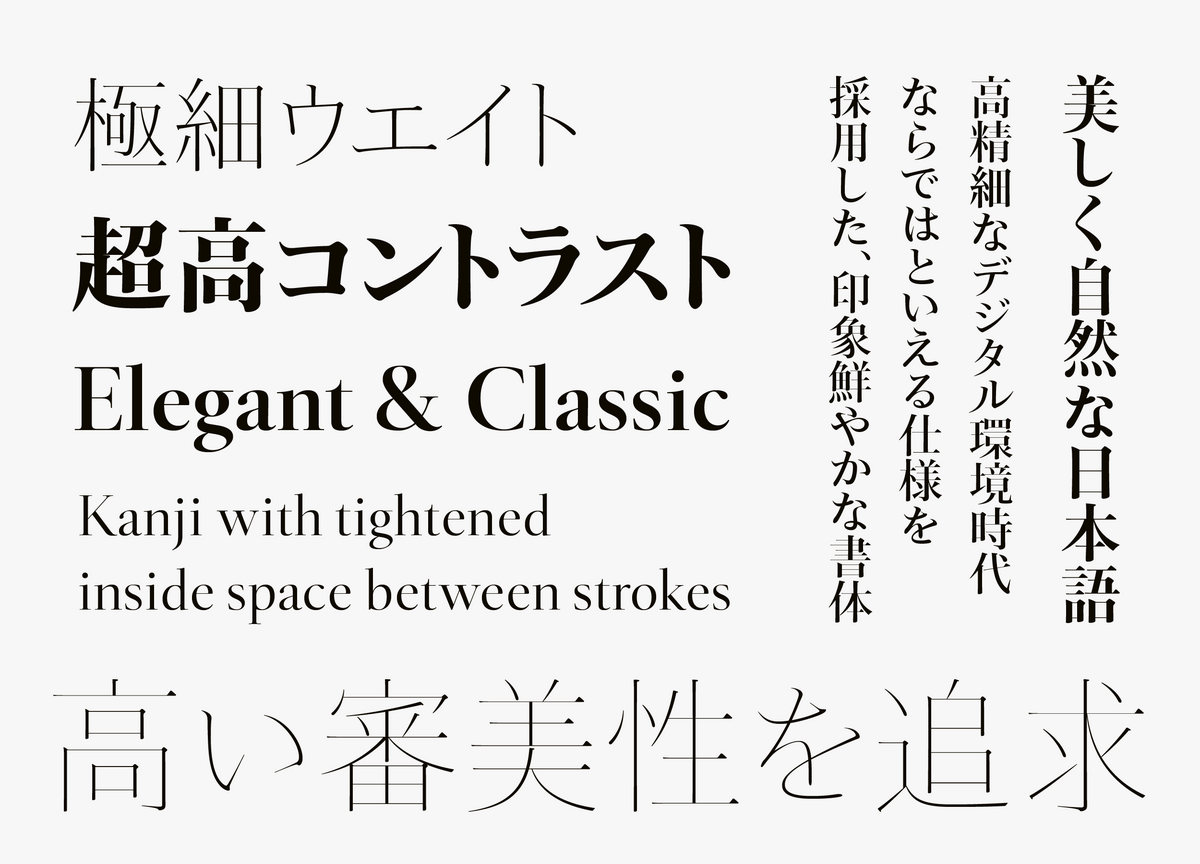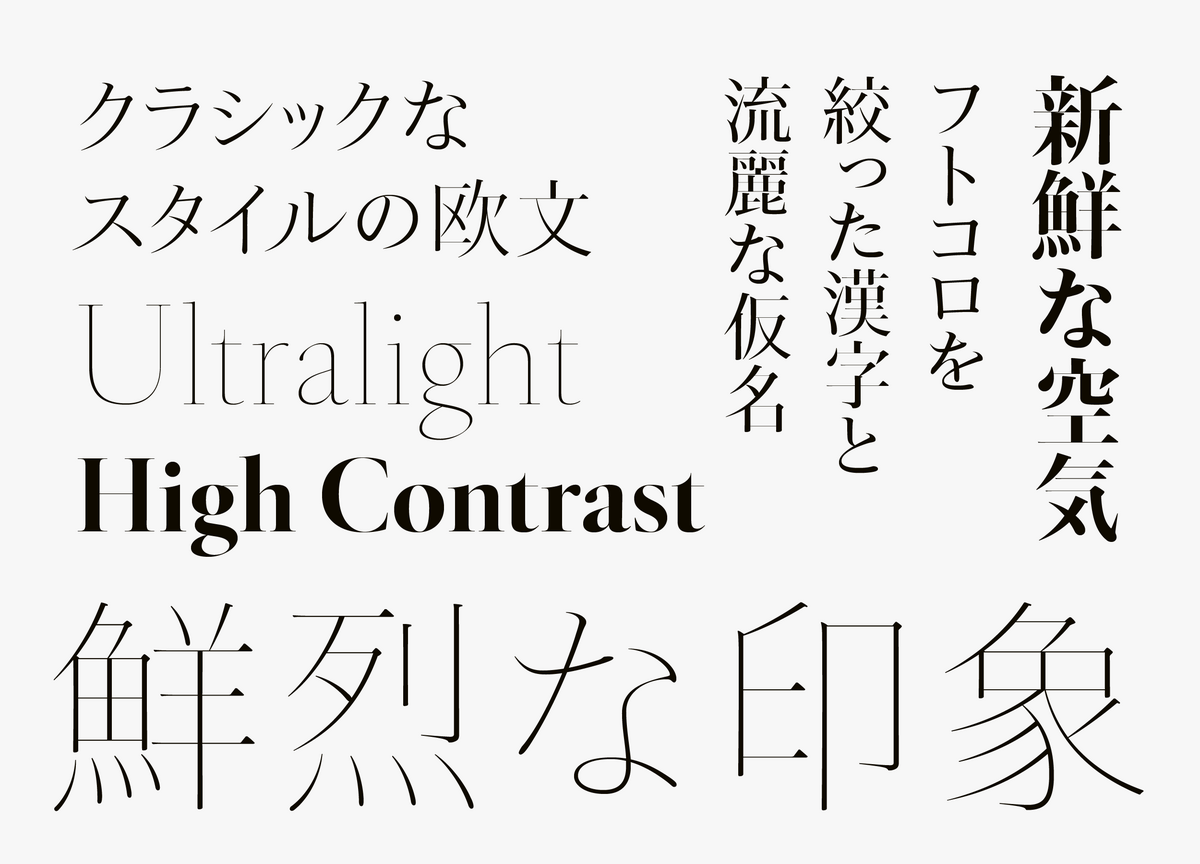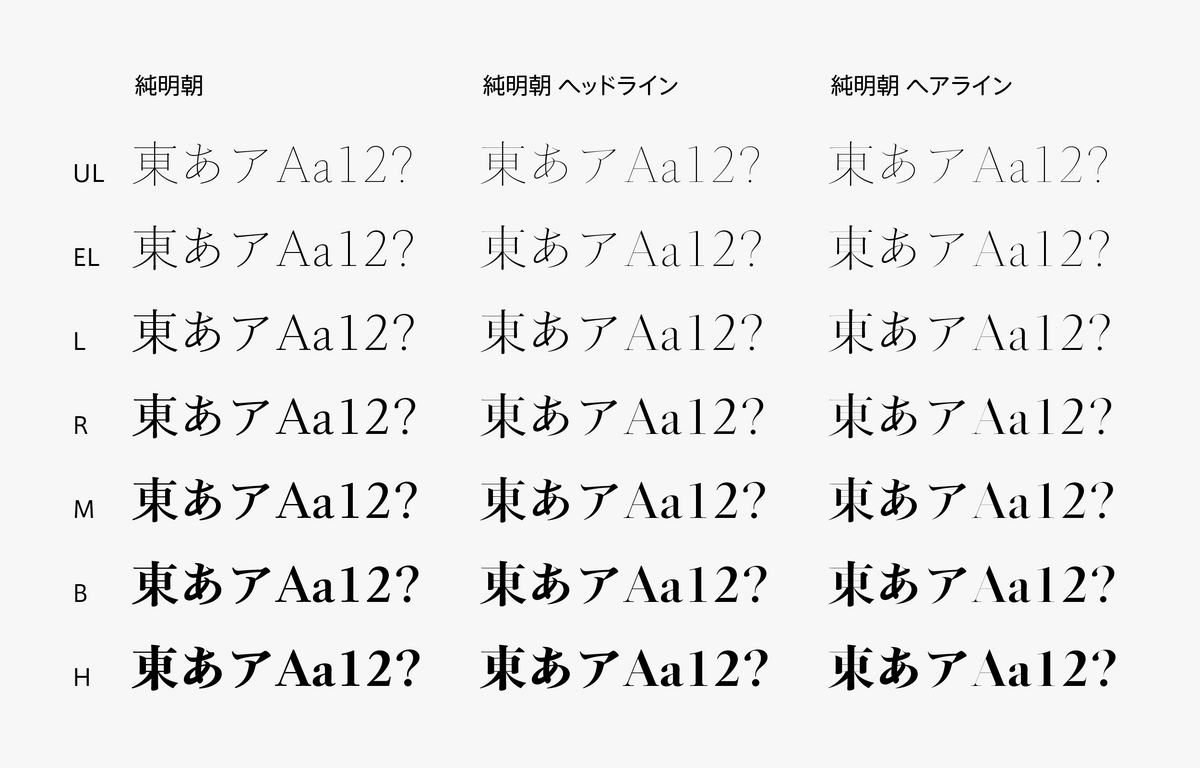
タイププロジェクトがコントラストを極限まで高めた「純明朝 ヘッドライン」 と「純明朝 ヘアライン」の提供を開始
タイププロジェクトは、デジタル環境に適した純明朝のシリーズとしてより高い審美性を追求した「純明朝 ヘッドライン」 と「純明朝 ヘアライン」を2024年1月30日に発表し、タイププロジェクトのサブスクリプションサービス「TPコネクト」にて提供を開始した。
「純明朝 ヘッドライン」と「純明朝 ヘアライン」は、横組みの日本語をもっと読みやすく、もっと美しくをテーマにした純明朝シリーズの中で、より高い審美性を追求するために開発した書体となる。
オーソドックスで汎用性の高い純明朝に対し、ヘッドラインとヘアラインは、ハライやテンの先端部を細くして縦画と横画のコントラスト比を高め、明朝体ならではの美しさを際立たせている。
▼純明朝 ヘッドライン
▼純明朝 ヘアライン
「純明朝 ヘッドライン」と「純明朝 ヘアライン」は、読みやすくて美しいという純明朝のコンセプトをベースに、見出し用途として思い切った設計を行った。
フトコロを絞った漢字と長めに残した平仮名の筆脈との相性が良いのはもちろんのこと、クラシックなスタイルの欧文が、優美な和文との調和を見せている。
「純明朝 ヘッドライン」と「純明朝 ヘアライン」は、高精細なデジタル環境時代ならではといえる仕様を採用した、印象鮮やかな書体となる。
タイププロジェクトの代表取締役 鈴木 功氏は、「純明朝 ヘッドラインとヘアラインは、極細の横画とストローク先端部に明確にその特徴を示しました。汎用性が高く、実用的な役割を果たす純明朝が中核に存在するため、ヘッドラインとヘアラインは、審美性の高さを求める方向にデザインを振り切ることができました。とくに細いウエイトは、タイププロジェクトが得意にしてきた『極細ウエイト、超高コントラスト』のひとつの到達点と言えると思います」と述べている。
「純明朝 ヘッドライン」と「純明朝 ヘアライン」は、UL(ウルトラライト)、EL(エクストラライト)、L(ライト)、R(レギュラー)、M(ミディアム)、B(ボールド)、H(ヘヴィ)の7ウエイトで構成している。
通常の明朝体にはない細さのULとELは、キャッチフレーズやヘッドラインで使用した場合に、強いインパクトを与える。
また、極限まで高いコントラストをもつBとHは、これまでの見出し明朝がもの足りなく感じるほど、鮮やかな印象をもたらすフォントとなる。
ウエイト:UL(ウルトラライト)、EL(エクストラライト)、L(ライト)、R(レギュラー)、M(ミディアム)、B(ボールド)、H(ヘヴィ)